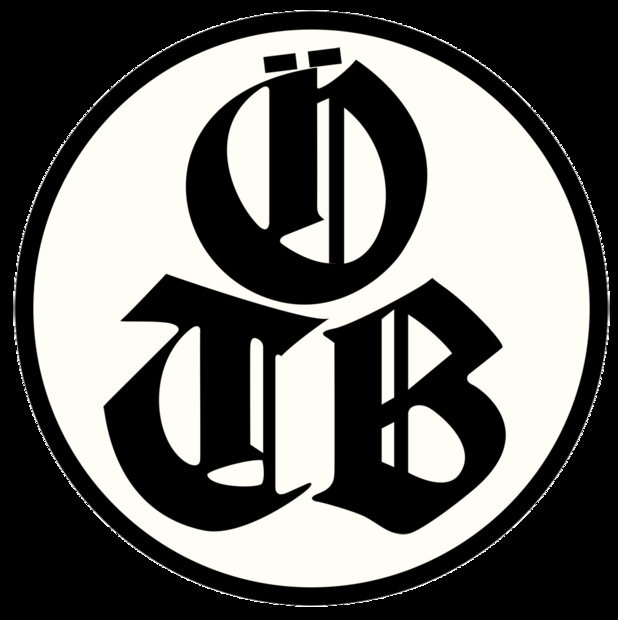
Fraktur: Österr. Turnerbund
Gezeichnet sind sie ganz bestimmt; die Ö-Striche passen in ihren Proportionen irgendwie nicht so recht dazu, auch die gegenläufige Neigung der »Kopfplatten« von T und B, die zusammen sozusagen eine Schale bilden, die das Ö trägt, spricht für eine gezeichnete Lösung. Ein T hätte diese Neigung »freiwillig« ganz bestimmt nicht. Das alles heißt freilich nicht, daß das gezeichnete Logo nicht eine Satzschrift als Vorbild hatte.
Gezeichnet sind sie ganz bestimmt;
Ja, natürlich. Du weißt, dass ich meinte: von Hand gezeichnet, ohne auf eine Satzschrift Bezug zu nehmen.
die Ö-Striche passen in ihren Proportionen irgendwie nicht so recht dazu, auch die gegenläufige Neigung der »Kopfplatten« von T und B, die zusammen sozusagen eine Schale bilden, die das Ö trägt, spricht für eine gezeichnete Lösung. Ein T hätte diese Neigung »freiwillig« ganz bestimmt nicht.
Aber welche Schrift Pate gestanden haben könnte, kann ich dir nicht sagen :-)